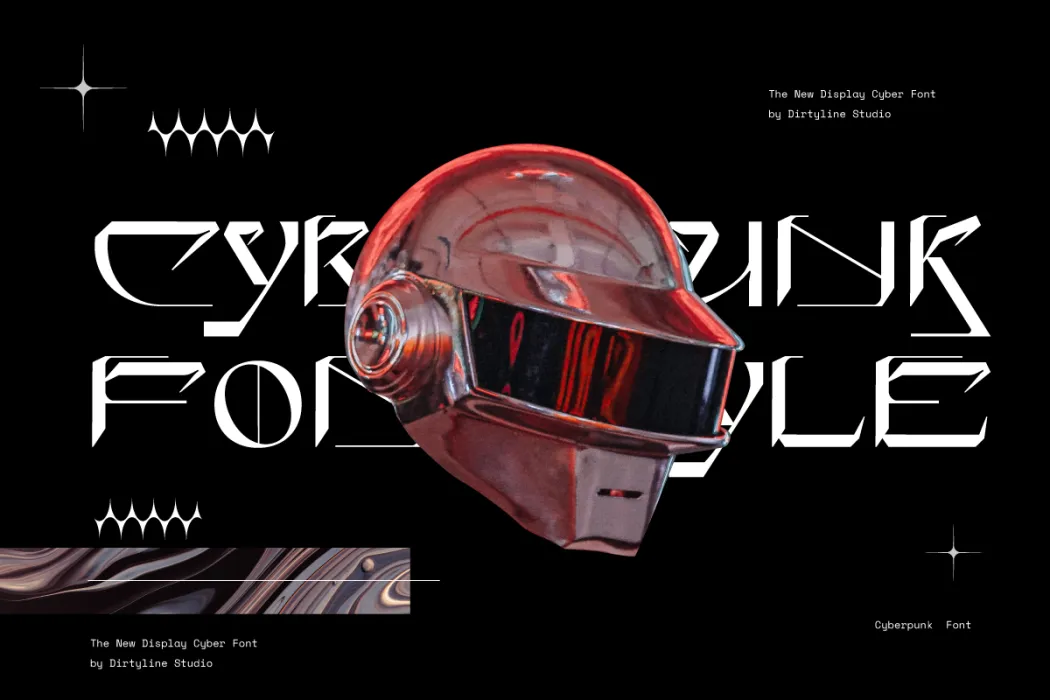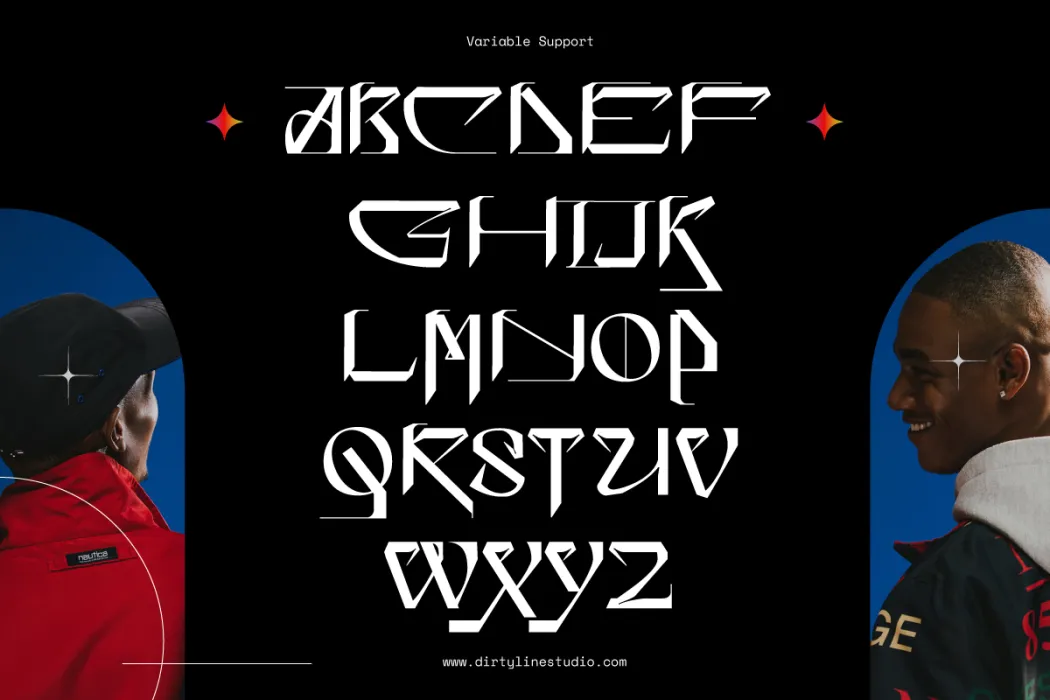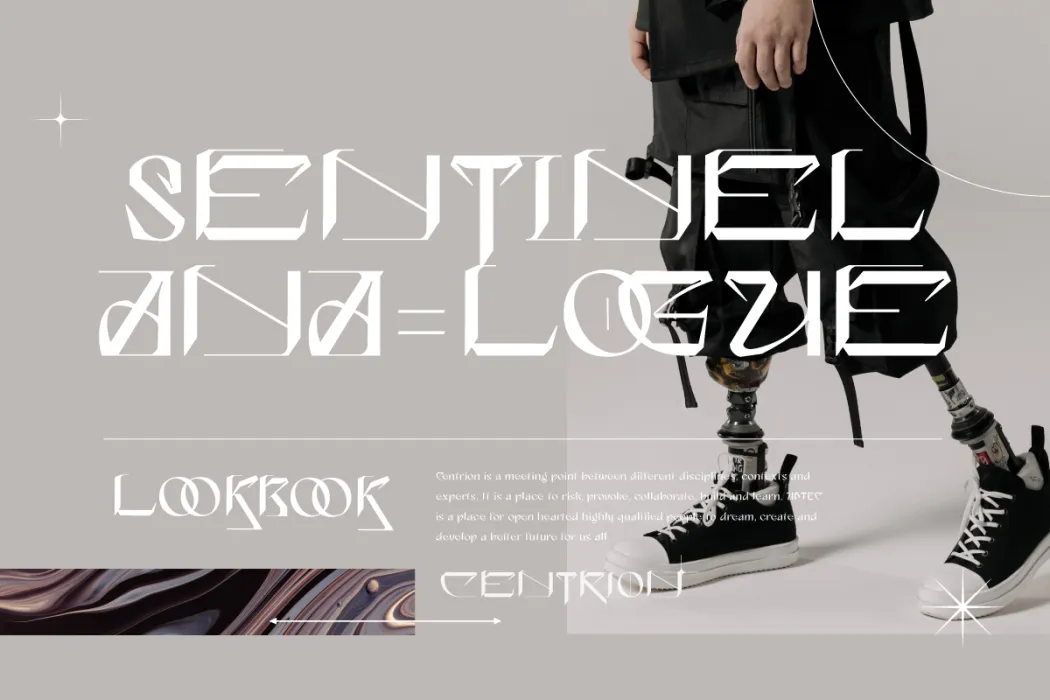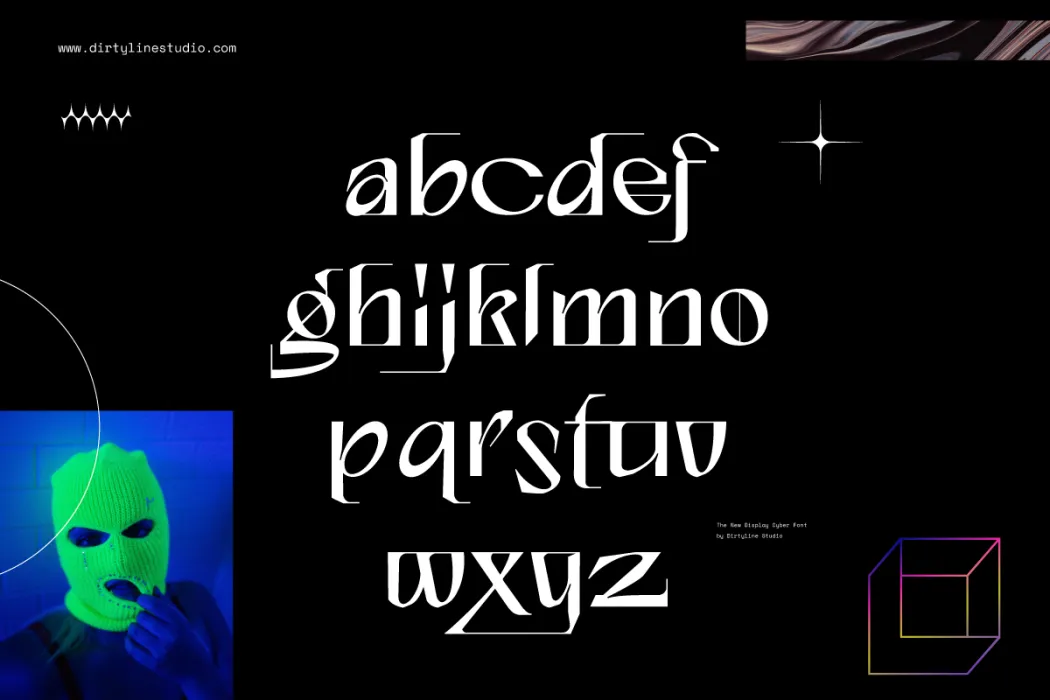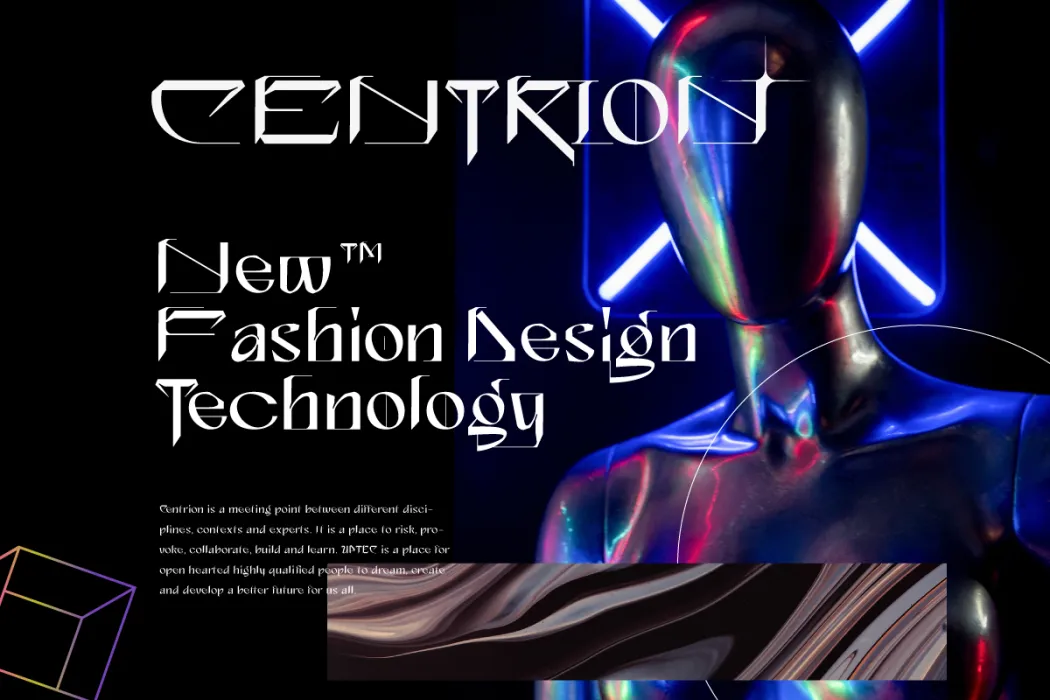
Centrion là Kiểu chữ Tương lai mới. lấy cảm hứng từ hình ảnh của thiết kế tương lai và dựa trên công nghệ từ các xu hướng mới nhất và sắp tới. Hoàn toàn phù hợp cho thương hiệu, thiết kế công nghệ, trò chơi, nội dung kỹ thuật số, giao diện người dùng, UX, áp phích tương lai, thiết kế typographic hiện đại, trang phục công nghệ , thiết kế xe cộ, ý tưởng nguyên mẫu, bất cứ điều gì bạn cần thúc đẩy cho tương lai.